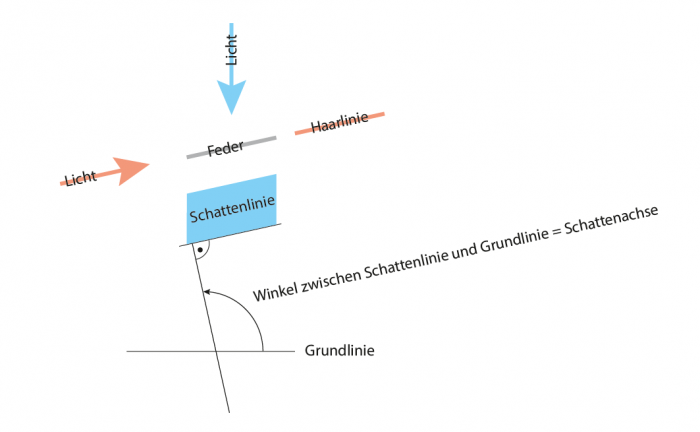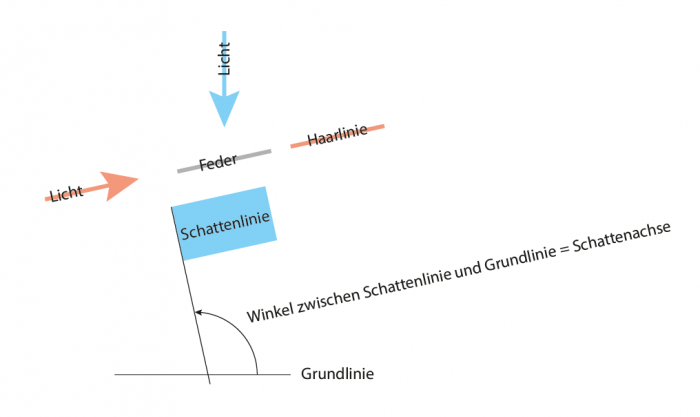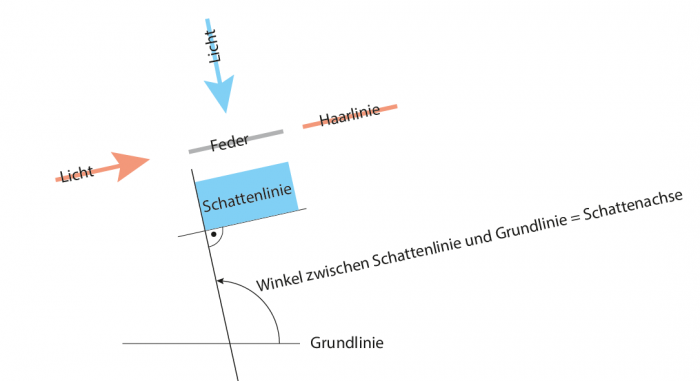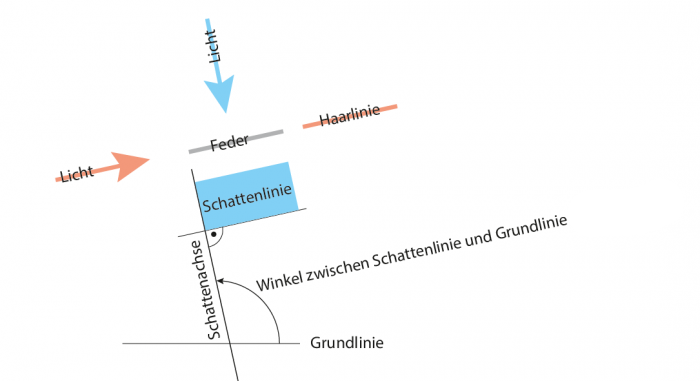
Wie erklärt man den Begriff »Schattenachse«?
Die Erklärung hier im Wiki ist leider keine gute. Da steht, sie käme durch die schräge Haltung »eines Schreibgerätes« zustande. Als Beispiel wird die Breitfeder genannt. Diese ist wohl auch das einzige Beispiel, abgesehen von anderen breiten Schreibgegenständen wie Flachpinseln, Holzspänen, Spachteln. Aber auch gezeichnete Schriften wie die klassizistischen haben Achsen. Und man kann auch mit einer Spitzfeder ohne sie zu drehen fettere Linien in einen Buchstaben zeichnen, da wäre jede Drehung vergebliche Mühe. Gar nicht erklärt wird, wie der »Schatten« in den Begriff kommt. Weiß das jemand? Ich dachte erst, der Begriff wäre aus der Astronomie übernommen worden, aber das ergibt keinen Sinn. Ich kann mir freilich nun alles mögliche zusammenreimen, etwa daß die stärkeren Bögen im Buchstaben als Schatten bezeichnet werden, zwischen denen eine Achse verläuft. In der Astronomie verläuft die Achse aber vom lichtwerfenden durch den schattenwerfenden Körper. Und der Begriff dürfte doch, denke ich mir einfach so, in der Astronomie zuerst dagewesen sein. Und zwei Schatten können sich schlecht gegenüberstehen, wenn in der Mitte das Licht ist. Also, bitte keine Spekulationen, das wäre zu einfach und würde kaum zur Antwort führen.
Ich kann einfach keine Erklärung für den Begriff finden. Woher kommt er und was bedeutet er im Wortsinn? Vielleicht ist sie ja ganz leicht. Es würde mir sehr helfen, wenn mir jemand ein Licht über dem Schatten meines Unwissens aufgehen lassen könnte und würde. Ein vermutungsfreies.
Ich habe mal gelernt, dass der Begriff von der Schattenlinie herrührt. Diese wiederum ergibt sich beim nahezu senkrechten Lichteinfall auf die Feder, im Gegensatz zur Haarlinie.
Schnell skizziert:
Müsste Dein blaues Rechteck nicht ein Parallelogramm sein? Dann würde der Winkel anders sein, nämlich 90°.
Vielen Dank für die Skizze. Ich kann das leider nicht verstehen. Warum gibt es auf der Zeichnung zwei Lichtquellen? Und wie wird aus einem Winkel eine Achse? Ich bin naturwissenschaftlich leider ein Analphabet. Traurig, aber wahr. Und wenn man ein breites Schreibgerät senkrecht von oben beleuchtet, bleibt der Schatten an jeder Stelle gleich. Er deckt sich mit den dicksten Stellen eines Kreises und er fällt von der dünnsten zur dünnsten Linie wie eine Achse. Aber warum sollte jemand eine Lampe lotrecht über ein Schreibgerät hängen? Damit sich da ein Schatten bildet und man die Achse Schattenachse nennen kann? Das kommt mir merkwürdig vor.
Ich weiß ja nicht, warum so wenige Antworten kommen, vielleicht ist meine Frage uninteressant. Oder wird der Begriff benutzt, ohne daß man ihn erklären könnte?
Ich finde den Begriff Schattenachse nicht vor dem Jahr 2000. In der älteren Literatur finde ich die Begriffe Schattenstrich und Haarstrich. Ansonsten wird von Achsen und Druckverteilung gesprochen. Aber nicht von Schattenachsen. Mich würde sehr interessieren, wie der Begriff in die Typografie kommt. Ich habe jetzt, im Moment, ein wenig den Eindruck, daß er da nichts zu suchen haben könnte. Was ja ein wenig peinlich wäre und nicht wünschenswert.
Ich habe jetzt, im Moment, ein wenig den Eindruck, daß er da nichts zu suchen haben könnte. Was ja ein wenig peinlich wäre und nicht wünschenswert.
Wieso das? Der Begriff hat eine klare Funktion und Definition – ich kenn noch nicht mal Synonyme. Ob es den Begriff in anderen Bereichen mit anderen Bedeutungen auch gibt, ist doch völlig irrelevant. So wie es uninteressant ist, dass der Duden für »Setzkasten« als erste Bedeutung »flacher Kasten für junge Gemüse- oder Blumenpflanzen« angibt.
Den Wiki-Artikel kann ich noch etwas optimieren. Da hast du recht. Er ist nicht falsch, aber lässt sich leicht missverstehen.
Müsste Dein blaues Rechteck nicht ein Parallelogramm sein? Dann würde der Winkel anders sein, nämlich 90°.
Ja, war auch nur schnell hingezeichnet. Ändert aber nichts an der Tatsache, dass der Winkel gemeint ist:
Ich finde den Begriff Schattenachse nicht vor dem Jahr 2000.
die älteste typografische quelle, die google books für ›Schattenachse‹ hat, ist von 1992 (ein buch, an dem albert kapr mitgewirkt hat). in den 50er- und 60er-jahren habe ich ›O-Achse‹ als bezeichnung für dieses phänomen entdeckt. ›Achse der Rundungen‹ bzw. ›Rundungsachse‹ ist auch aus den 60er-jahren. in jüngster zeit begegnet man bisweilen ›Symmetrieachse‹.
mich würde auch interessieren, wodurch die bezeichnung als schattenachse motiviert war. wo fällt denn da ein schatten? aus der zeichnung von bertel werde ich übrigens auch nicht recht schlau. an der verwendung des begriffs ändert das aber, wie ralf schon sagte, nichts. man nennt es nun einmal so und jeder weiß, was gemeint ist.
An der Verwendung des Begriffs änderte es schon etwas, wenn man ihn nicht erklären könnte.
Bertel, würdest du mal ein Garamond-o in die Zeichnung setzen? Ich verstehe sie beim besten Wille nicht. Mit einem Buchstaben sieht man vielleicht besser.
Müsste Dein blaues Rechteck nicht ein Parallelogramm sein? Dann würde der Winkel anders sein, nämlich 90°.
Ja, war auch nur schnell hingezeichnet. Ändert aber nichts an der Tatsache, dass der Winkel gemeint ist:
post-14085-0-13219200-1422966960_thumb.p
Vielen Dank für die Skizze. Ich kann das leider nicht verstehen. Warum gibt es auf der Zeichnung zwei Lichtquellen? Und wie wird aus einem Winkel eine Achse? Ich bin naturwissenschaftlich leider ein Analphabet. Traurig, aber wahr. Und wenn man ein breites Schreibgerät senkrecht von oben beleuchtet, bleibt der Schatten an jeder Stelle gleich. Er deckt sich mit den dicksten Stellen eines Kreises und er fällt von der dünnsten zur dünnsten Linie wie eine Achse. Aber warum sollte jemand eine Lampe lotrecht über ein Schreibgerät hängen? Damit sich da ein Schatten bildet und man die Achse Schattenachse nennen kann? Das kommt mir merkwürdig vor.
Ich weiß ja nicht, warum so wenige Antworten kommen, vielleicht ist meine Frage uninteressant. Oder wird der Begriff benutzt, ohne daß man ihn erklären könnte?
Du mußt nicht versuchen, mich für meine Fragen zu dikreditieren, weil du die Antworten nicht weißt. Und wenn du die Antworten nicht wissen willst, sind sie allein deshalb nicht für jedermann unnötig.
Ich diskreditiere deine Fragen nicht. Schon gar nicht, weil ich die Antworten nicht weiß oder nicht wissen will. Was sind das für komische Unterstellungen?